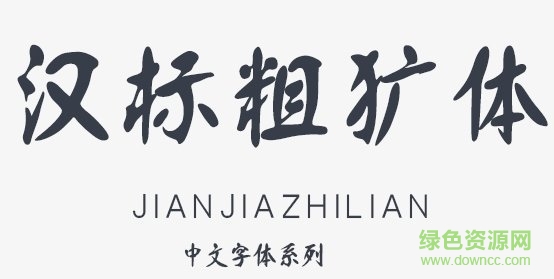
漢標(biāo)粗獷體
漢標(biāo)粗獷體字體是漢標(biāo)字體中一款十分大氣張揚(yáng)的毛筆書法字體,結(jié)構(gòu)勻稱有氣勢(shì),造型簡(jiǎn)潔而大氣,給人留下深刻印象,來綠色資源網(wǎng)添加新字體吧!
漢標(biāo)粗獷毛筆字體特色
漢標(biāo)粗獷體字體端正大方,線條簡(jiǎn)潔利落,筆鋒粗曠,帶有行楷的手寫書法風(fēng)格,是一款優(yōu)秀且耐看的中文字體。
漢標(biāo)粗獷字體字如其名,毫無保留的講毛筆書法的粗獷飄逸的風(fēng)格盡情展現(xiàn),讓你的設(shè)計(jì)兼具古風(fēng)和藝術(shù)字體的美感,可適用于平面設(shè)計(jì)、網(wǎng)頁設(shè)計(jì)、報(bào)刊雜志、影視字幕、廣告大字等領(lǐng)域。